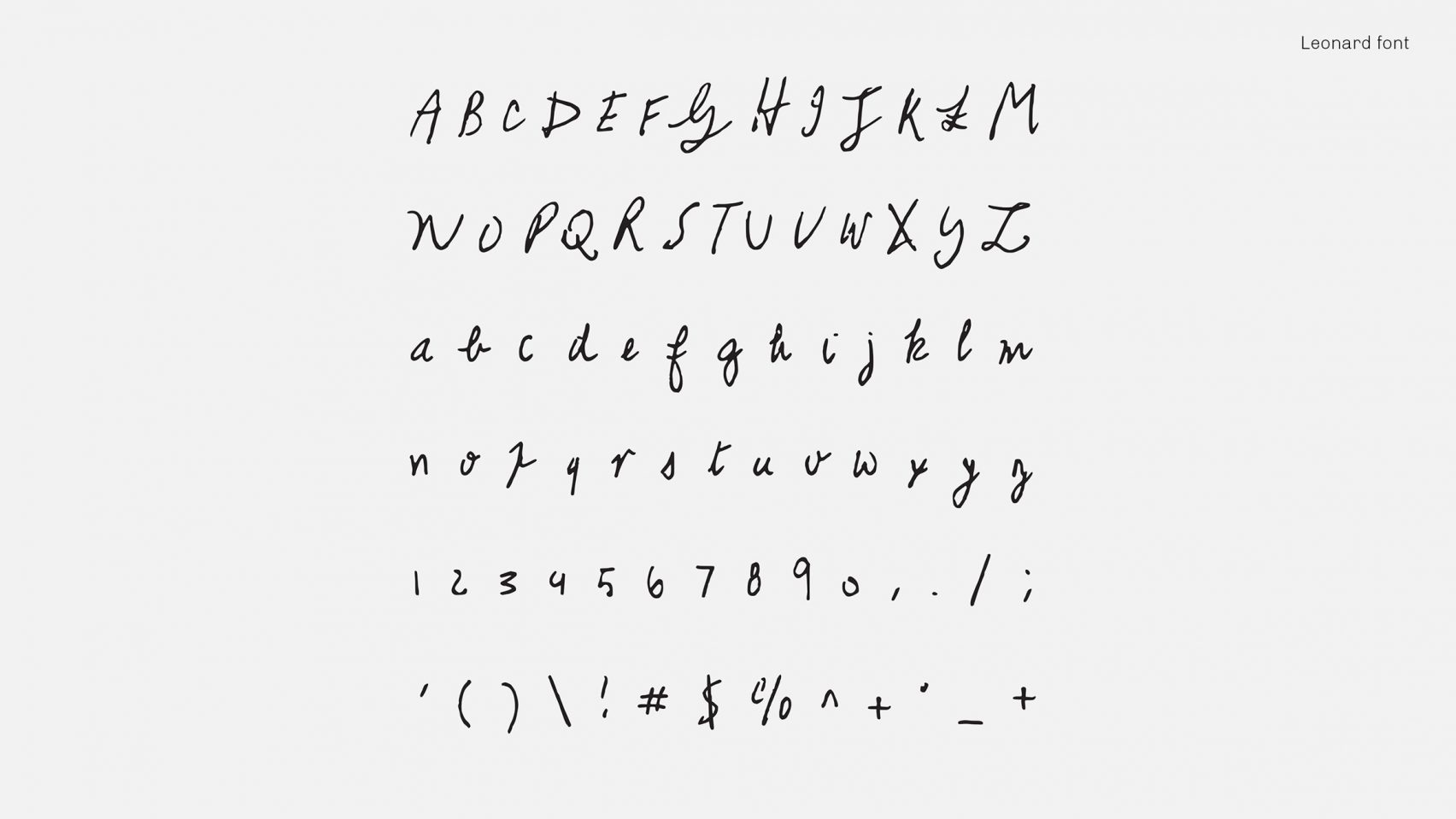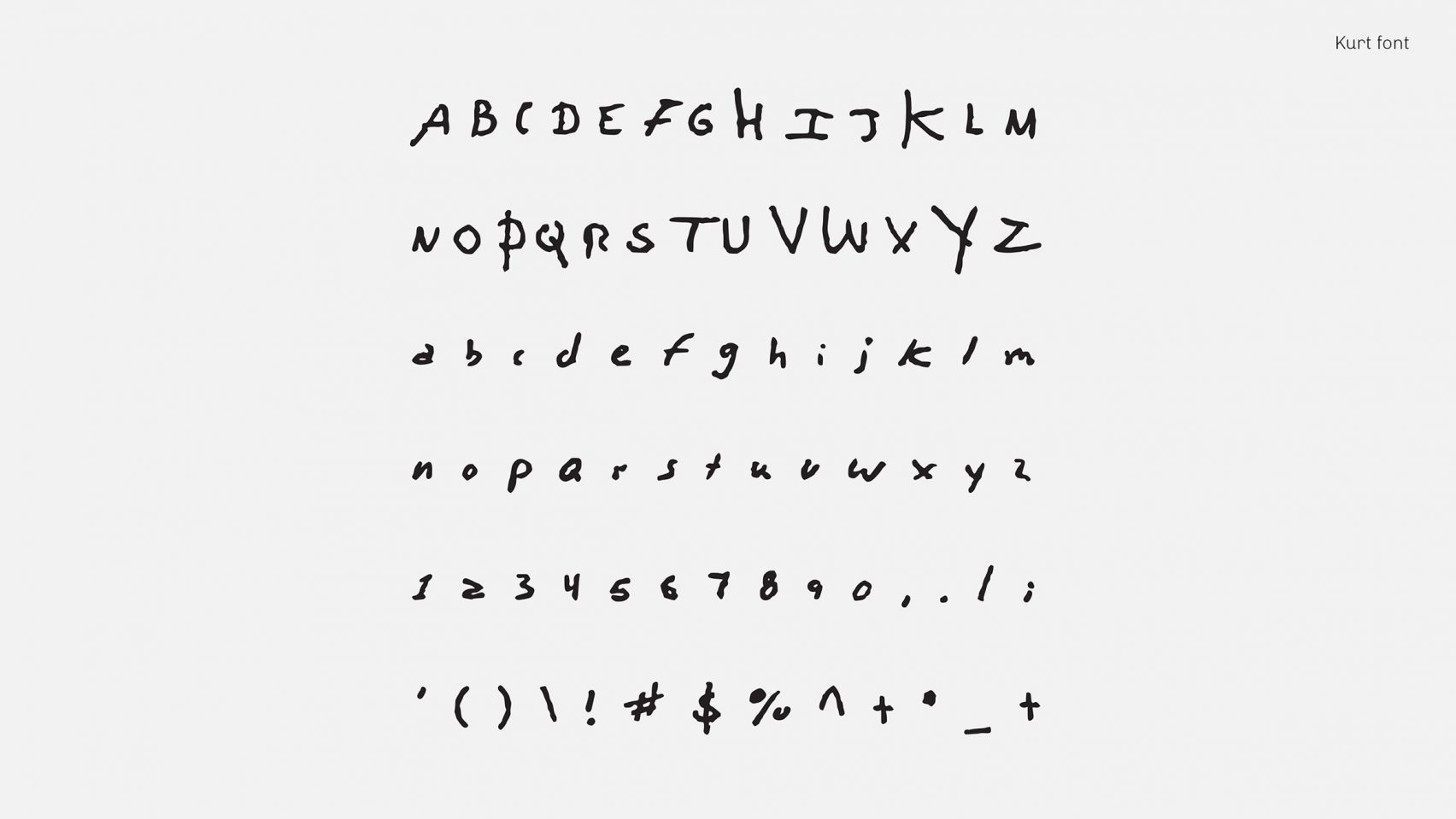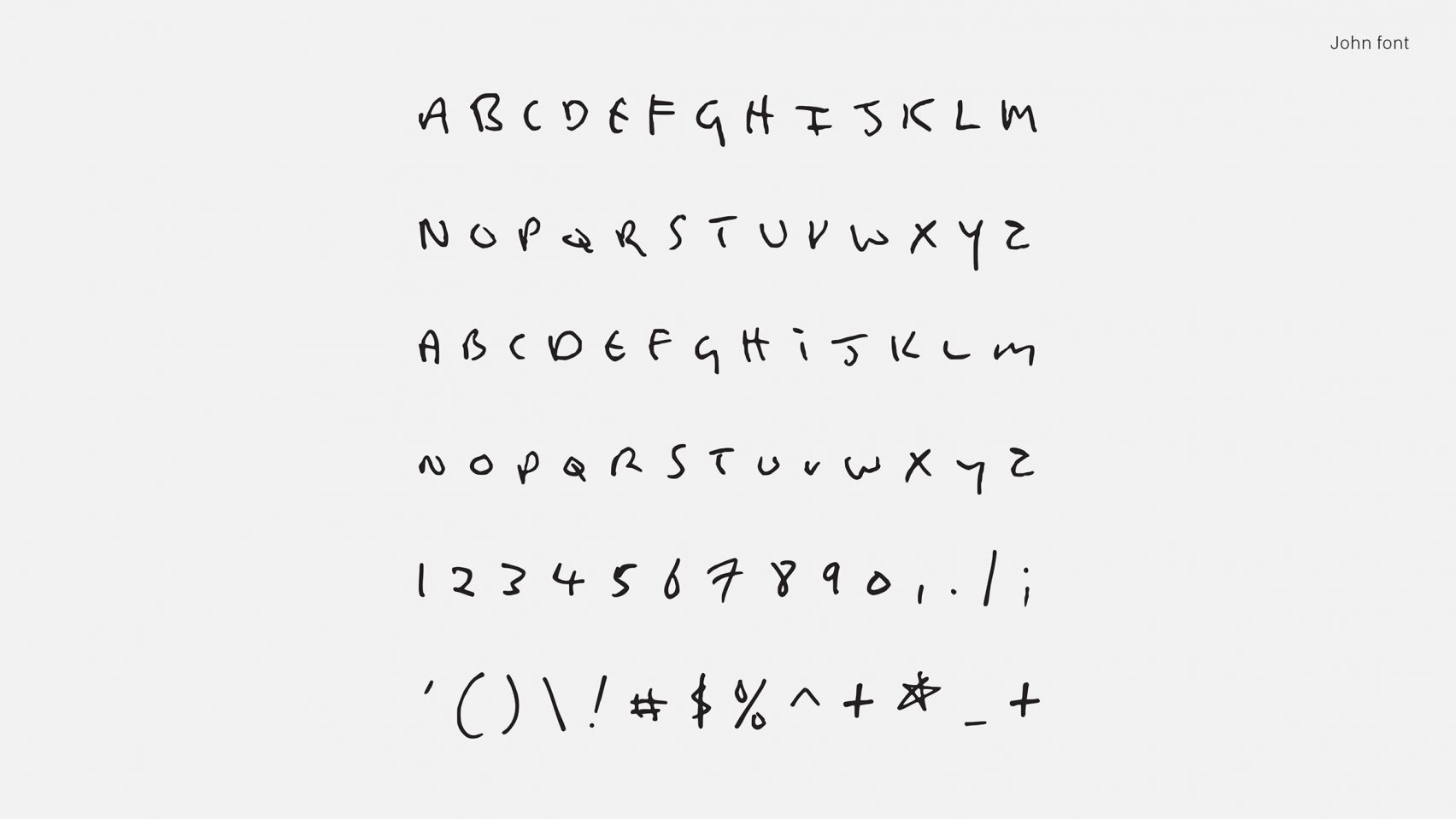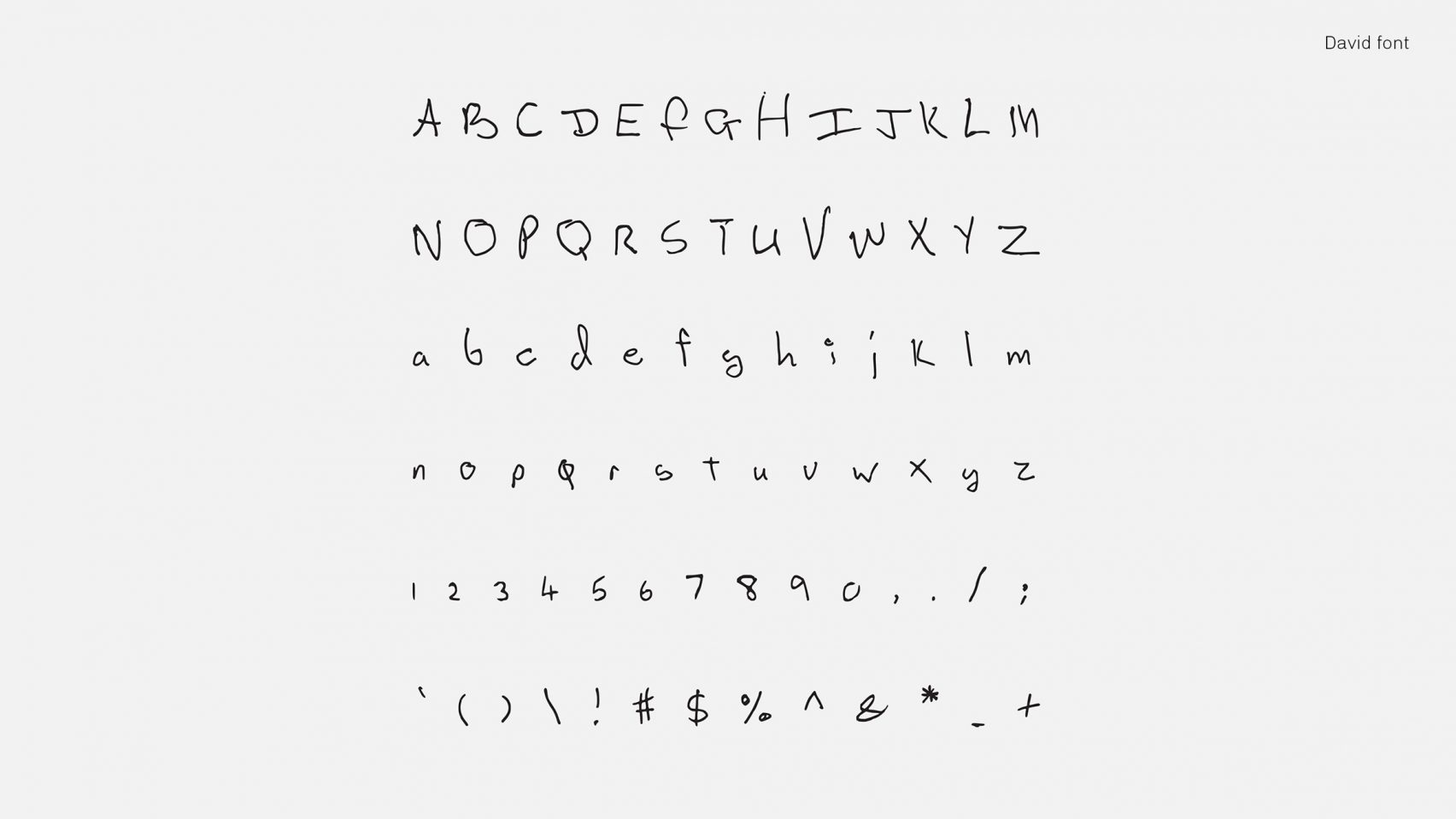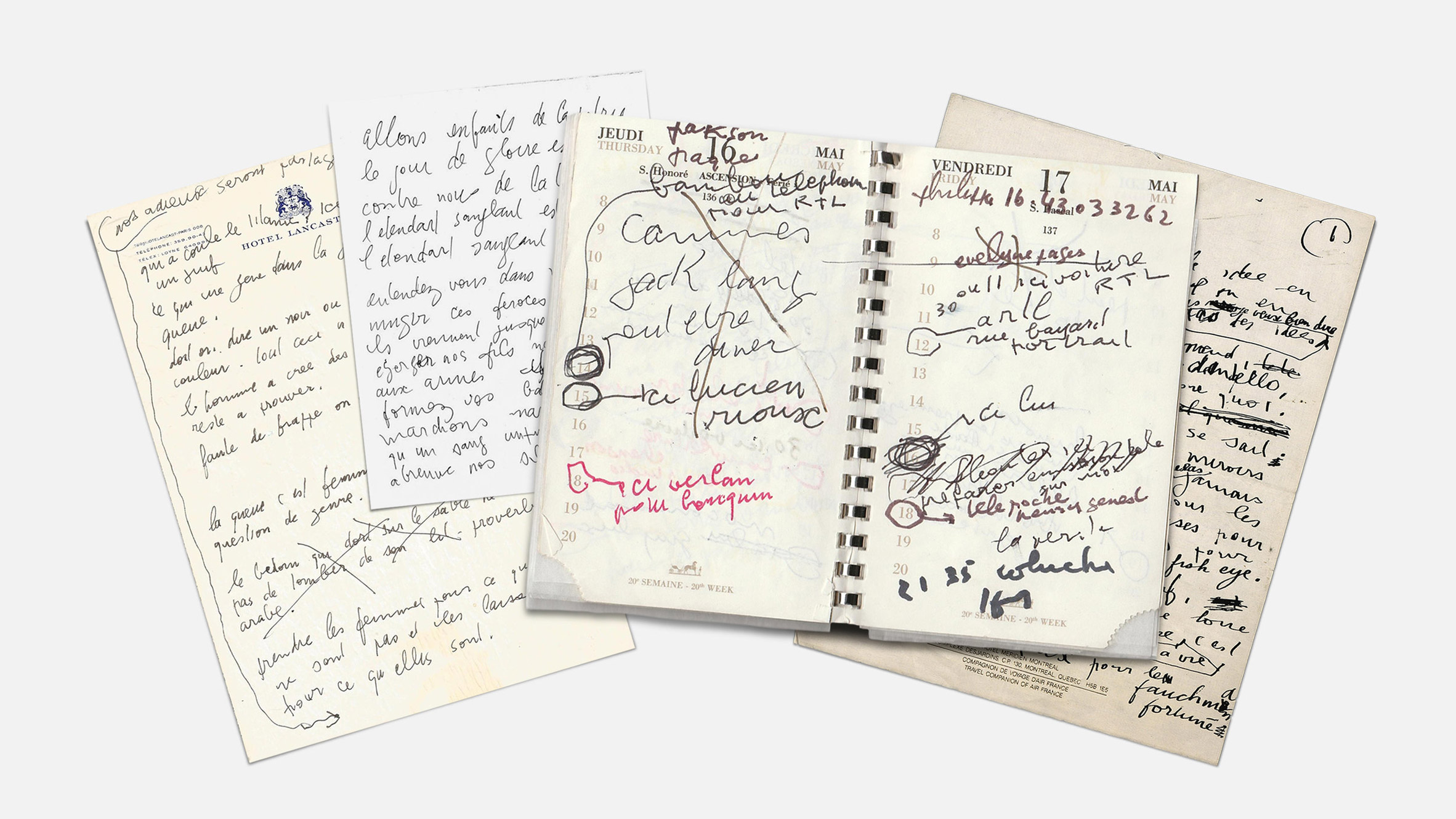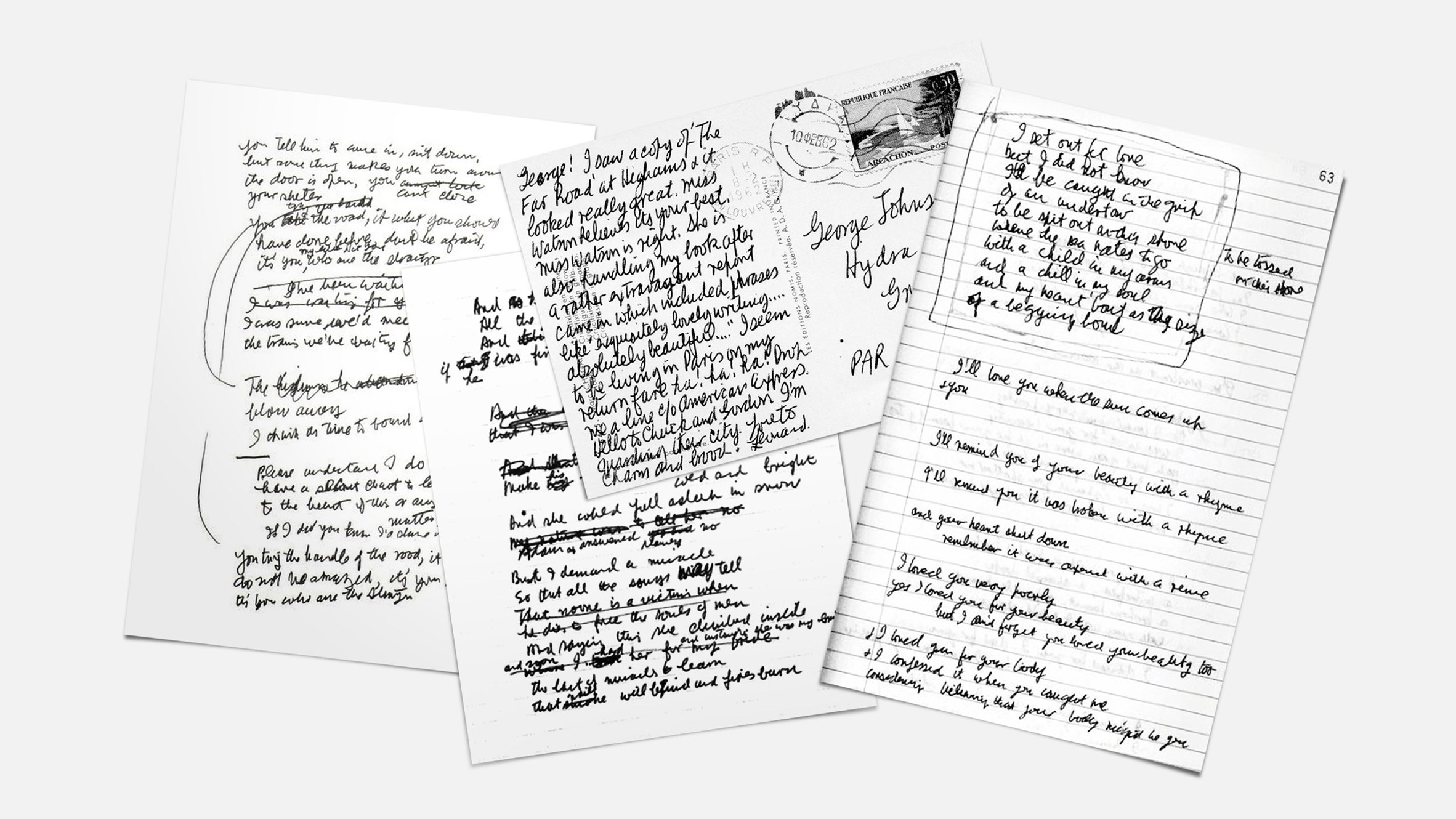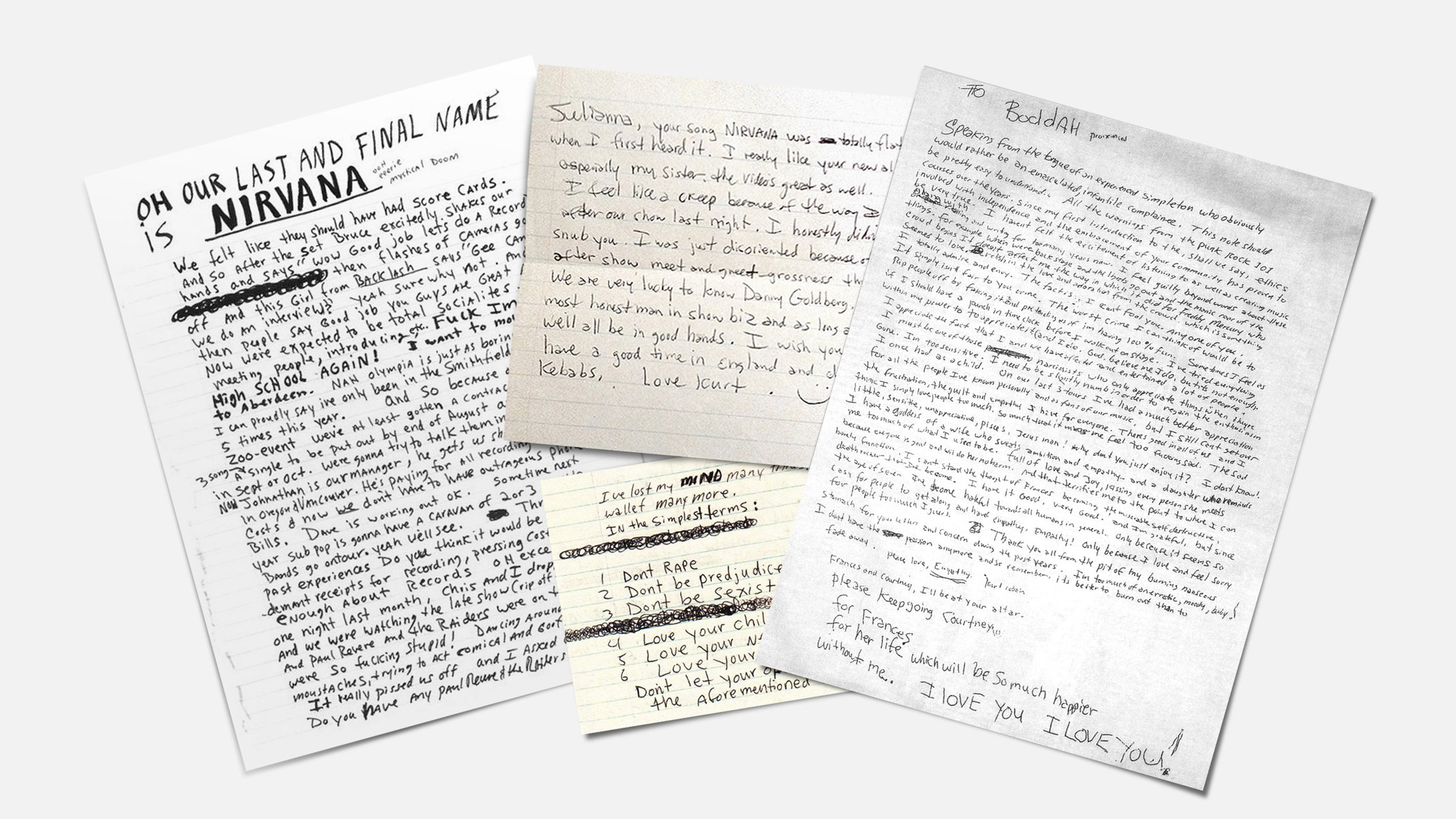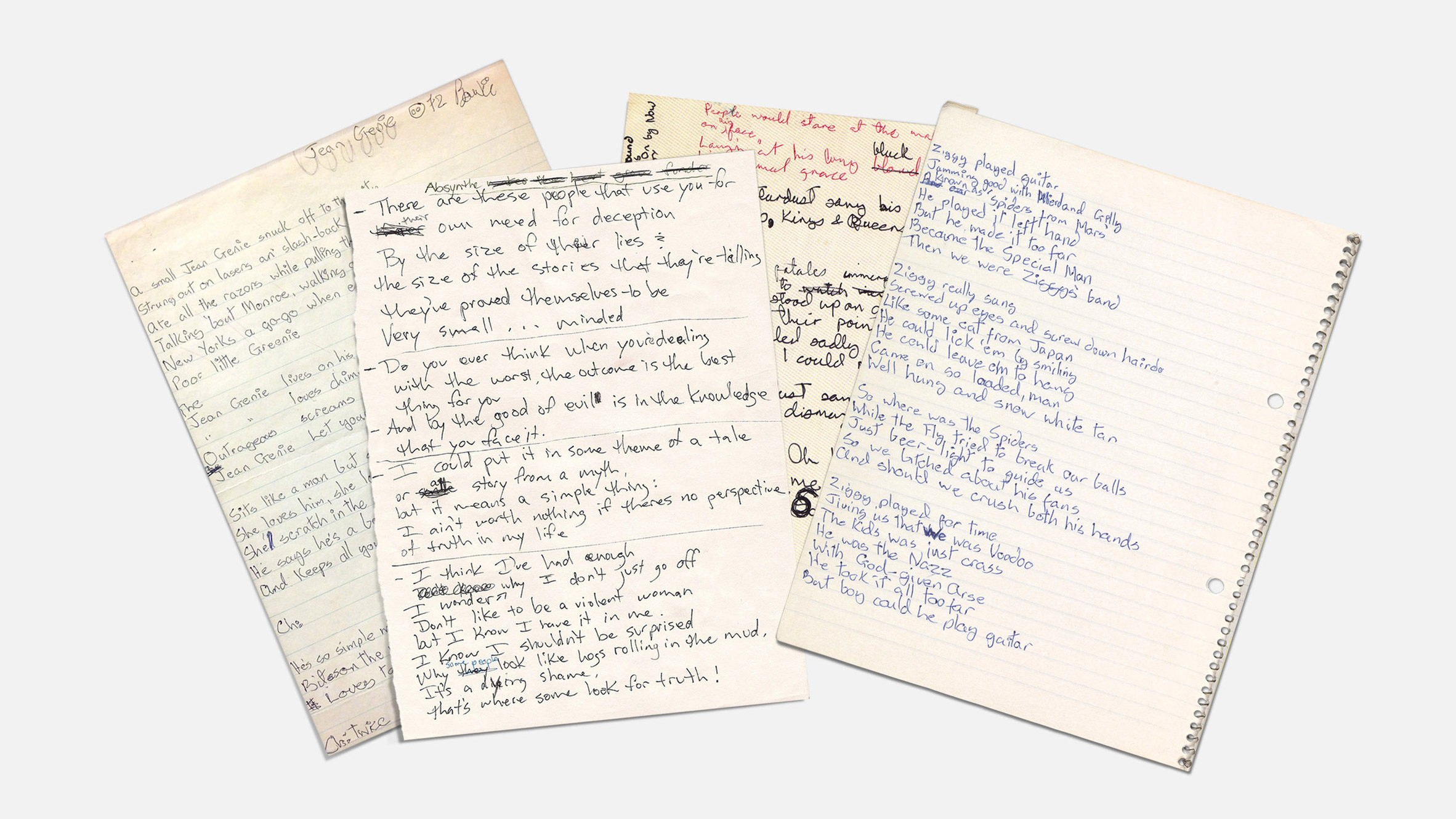
Nếu là fan của những nghệ sĩ nổi tiếng này chắc hẳn bạn sẽ phải rất vui mừng vì có thể sử dụng được bộ chữ của thần tượng để tạo nên những tác phẩm riêng cho mình.
2 nhà thiết kế đồ họa người Pháp là chị Julien Sens và anh Nicolas Damiens đã chuyển đổi chữ viết tay của huyền thoại ca sĩ nhạc rock David Bowie, John Lennon, Kurt Cobain, Leonard Cohen và Serge Gainsbourg thành những font chữ viết tay.
Font viết tay của Leonard
Bộ chữ này được gọi là Songwriter Fonts các bộ chữ sẽ có chữ cái, số, biểu tượng của từng nghệ sĩ một. Điều này sẽ truyền cảm hứng rất lớn đến những người nhạc sĩ thông qua chữ viết tay của những “tượng đài” mà họ yêu thích.
Sens và Damiens nói:
Chúng tôi phát triển các font chữ của nhà soạn nhạc với ý tưởng rằng nó có thể giúp trí tưởng tượng của một nhà soạn nhạc phát triển bằng cách viết bằng chữ viết tay cho các nhạc sĩ huyền thoại – giống như chơi trên cây đàn piano của John Lennon hay Kurt Cobain.
Bộ chữ của Lennon
Sen và Damiens chia sẻ:
Chúng tôi phát triển các font chữ Nhà soạn nhạc (Songwriter Fonts) này với ý tưởng muốn giúp những nhạc sĩ khác có thể phát huy trí tưởng tượng, được truyền cảm hứng thông qua những con chữ của các huyền thoại âm nhạc – kiểu giống như là họ đang chơi trên chính chiếc đàn piano của Lennon hoặc đàn ghita của Kurt Cobain vậy.
Chữ của Kurt được làm lại
Họ nói tiếp:
Điều này không có nghĩa là bạn sẽ giỏi như họ nhưng nó sẽ giúp bạn có được một tâm trạng đặc biệt “thăng hoa” hơn và có lẽ bạn sẽ được truyền những nguồn cảm hứng mới lạ hơn khi nghĩ về họ.
Các nhà thiết kế bắt đầu bằng cách nghiên cứu các khá nhiều các tài liệu viết tay từ nhiều nguồn, trên web, thư viện công cộng cho đến cả bức thư tự sát nổi tiếng của Kurt Cobain.
Font chữ của David
Đầu tiên là phải tìm ra thật nhiều tài liệu viết tay càng tốt để có đủ ký tự tạo thành 1 bảng chữ cái của riêng từng người. Đó là công việc tốn thời gian nhất nhưng sau đó chúng tôi rất vui vì đã có thể tìm được những con chữ bị mất sau hàng giờ đồng hồ tìm kiếm.
Mỗi biểu tượng được làm lại bằng kỹ thuật số dựa trên phần mềm làm font chữ. Các nhà thiết kế cũng cho biết: “Làm lại bộ chữ cho Leonard Cohen và Serge Gainsbourg là vất vả nhất bởi chúng tôi phải mất nhiều thời gian để định hình lại từng con chữ một để chúng có thể ghép lại với nhau một cách hợp lý.”
Một số tài liệu mà 2 nhà thiết kế đồ họa tìm được
Một số hình ảnh khác về những tài liệu viết tay mà họ đã tìm được: